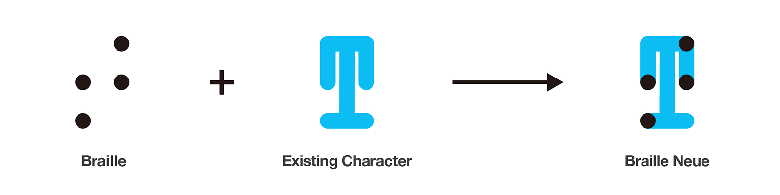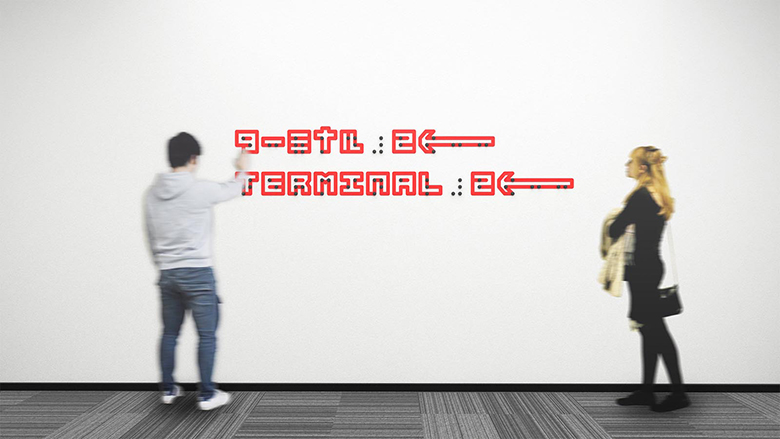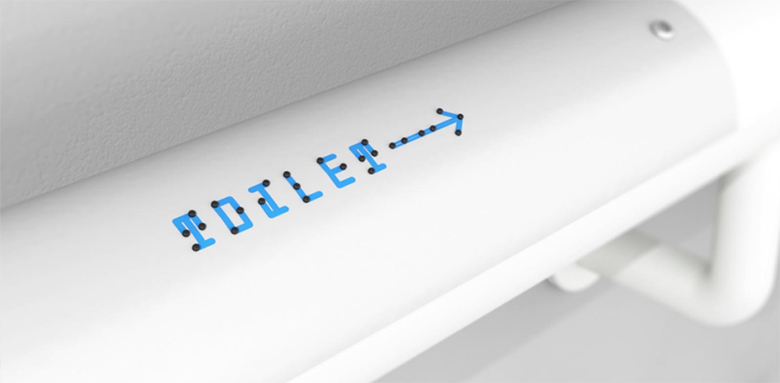
فونت خلاقانهای که همزمان برای نابینایان و افراد عادی قابل خواندن است
طراح خلاق توکیویی سعی کرده خط بریل را با الفبای انگلیسی و ژاپنی ترکیب کند تا هم بیشتر از گذشته در معرض دید نابینایان قرار گیرند و هم رسانههای چاپی بتوانند مطالبی برای نابینایان به سادگی منتشر کنند.
این فوت به نام Braille Neue معرفی شده است و از ایده ترکیب الفبای انگلیسی با همان المانها و علامتهای خط بریل ساخته میشود. نقاط بریل روی حروف قرار میگیرند و اینگونه برای رسانهها سادهتر میشود یک پیغام یا متن را در فضایی کوچکتر منتشر کنند.
مزیت این متن در این است که هم افراد عادی میتوانند آن را بخوانند و هم افراد نابینا یا کم بینا قادر به درک و خواننداش خواهند بود. پیش از این؛ رسانههای چاپی ناچار بودند یک متن خبری را دوباره به صورت بریل برای افراد نابینا پیادهسازی کند.
تاکاشی ابتدا از فونت و سبک طراحی الفبای Helvetica Neue الهام گرفته و بعد سعی کرده هر کاراکتر را با دستکاری و تغییر به شکلی دربیاورد که کاراکتر خط بریل نیز روی آن بنشیند و برهم تطابق داشته باشند.
این پروژه دارای دو فونت اصلی است: Braille Neue که شامل کاراکترهای زبان انگلیسی است و فونت Braille Neue Outline که هم کاراکترهای زبان انگلیسی را پشتیبانی میکند و هم شامل حروف زبان ژاپنی است.
فونت Braille Neue برای استفاده در مکانهای عمومی و فضاهای بزرگ مانند بیلبوردها، تابلوهای تبلیغاتی، راهنماهای عمومی و غیره مناسب است. این فونت اجازه میدهد خط بریل میان مردم و جامعه بیاید و نابینایان در شهر هم بتوانند با بخشهای مختلف تعامل داشته و اطلاعاتی را دریافت کنند.